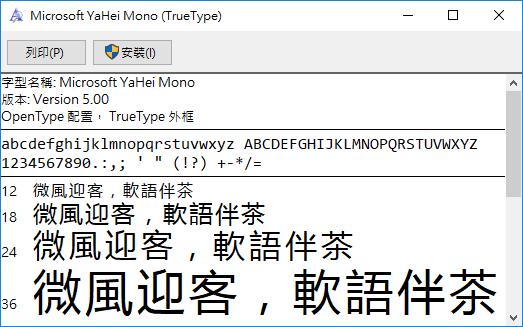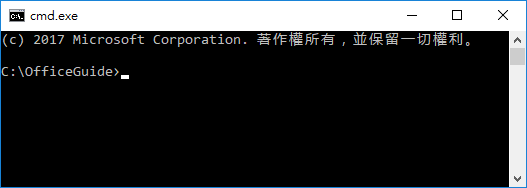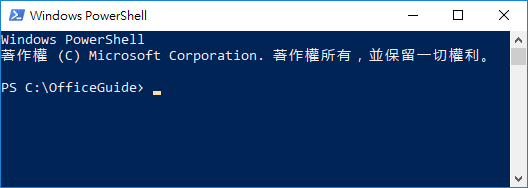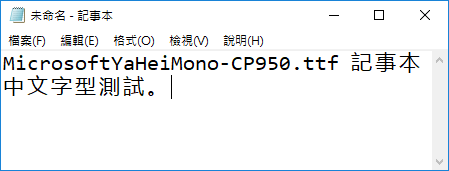
安裝並設定使用微軟雅黑字型,讓命令提示字元(cmd)與 PowerShell 的文字更美觀。
命令提示字元(cmd)與 PowerShell 的點陣字型雖然清晰,但是卻不夠美觀。如何讓字體更好看一點,同時也適合眼睛閱讀?
更改好字型之後,命令提示字元與 PowerShell 的字體就變得更好看了。
這套微軟雅黑字型也可以用在記事本、Notepad++ 或 Visual Studio Code 等各種文字編輯器中,只要修改這些軟體的字型設定即可。
這是在記事本中使用微軟雅黑字型的樣子。